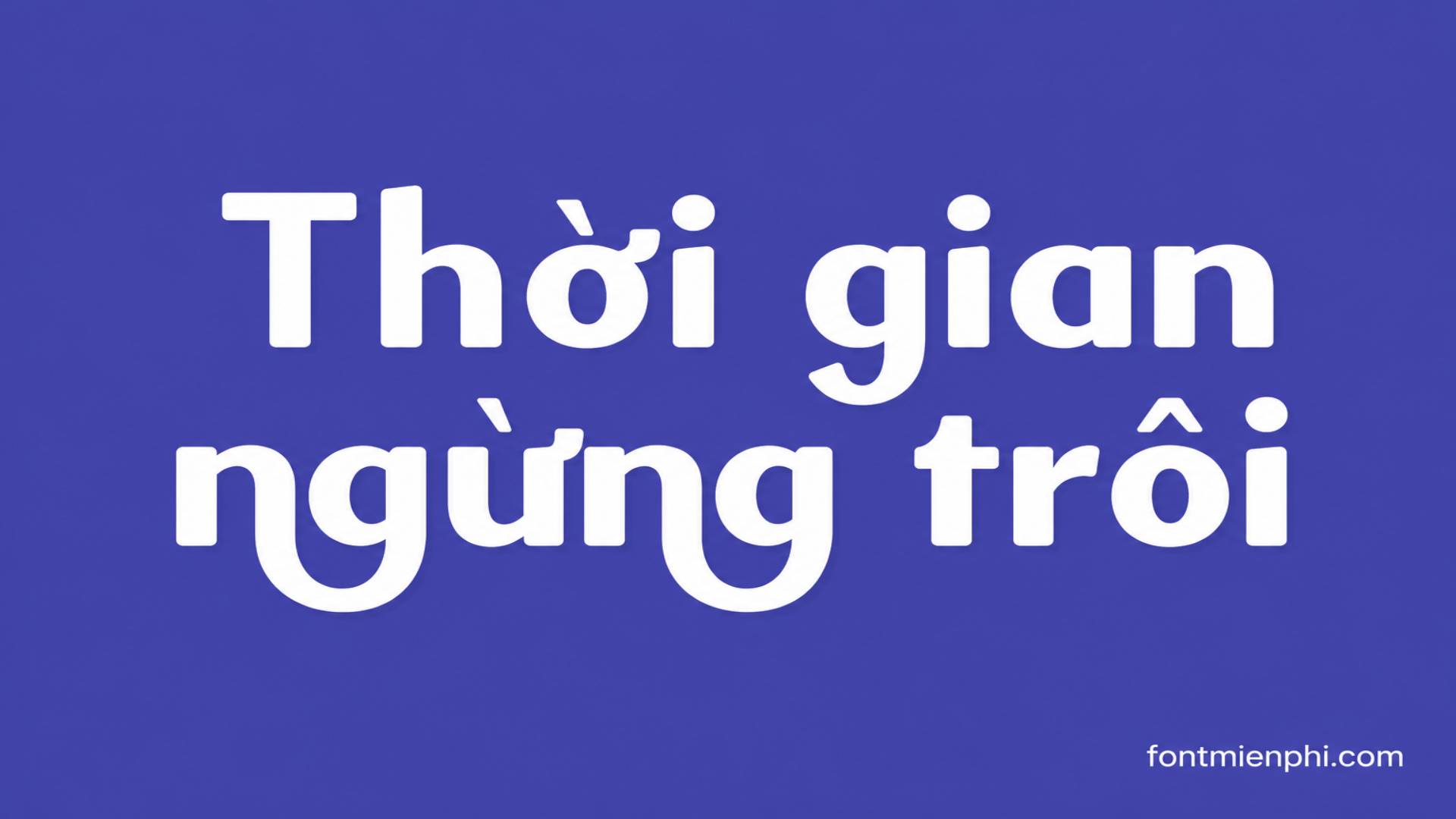
Bạn là một Content Creator, Designer hay Video Editor đang tìm kiếm một phông chữ hiện đại, cá tính để làm nổi bật các dự án sáng tạo của mình? Font Việt hóa 1FTV Creator Genius sinh ra chính là để dành cho bạn. Đúng như tên gọi “Thiên tài sáng tạo”, bộ font này mang đến một luồng gió mới với những đường nét phá cách, khỏe khoắn nhưng vẫn giữ được độ sắc nét và dễ đọc tuyệt đối.
1. Tổng quan về Font 1FTV Creator Genius
1FTV Creator Genius là một phông chữ mang phong cách hiện đại, năng động và đậm chất công nghệ. Khác với những phông chữ truyền thống cứng nhắc, Creator Genius được thiết kế với các đường nét dứt khoát, hình khối rõ ràng, tạo ra một nguồn năng lượng thị giác mạnh mẽ. Đây là kiểu chữ hoàn hảo để thu hút sự chú ý trong kỷ nguyên của mạng xã hội và nội dung số.
Hiểu được nhu cầu thiết kế đa dạng của người dùng Việt, đội ngũ 1FTV đã tiến hành Việt hóa chi tiết bộ font này. Hệ thống dấu câu tiếng Việt được vẽ lại tỉ mỉ, đảm bảo tỷ lệ cân đối với các chữ cái gốc. Sự tinh chỉnh này giúp người dùng dễ dàng gõ các tiêu đề, thông điệp bằng tiếng Việt một cách mượt mà mà không lo gặp lỗi “nhảy” font hay lệch dấu.
2. Những điểm sáng của Font Creator Genius Việt Hóa
Bộ font này nhanh chóng chiếm được cảm tình của giới thiết kế đồ họa và làm video nhờ những ưu điểm nổi bật sau:
• Phong cách sáng tạo, dẫn đầu xu hướng (Trendy & Modern): Mang đậm hơi thở của tương lai, công nghệ và sự phá cách, giúp thiết kế của bạn thoát khỏi sự nhàm chán thường thấy.
• Tối ưu hiển thị kỹ thuật số (Digital Display): Cấu trúc chữ được tính toán kỹ lưỡng để hiển thị cực kỳ sắc nét trên mọi loại màn hình, từ smartphone nhỏ gọn đến màn hình máy tính độ phân giải cao.
• Kerning Tiếng Việt chuẩn xác: Khoảng cách giữa các ký tự có dấu được xử lý hoàn hảo, không bị đứt gãy hay chồng chéo lên nhau, mang lại trải nghiệm đọc dễ chịu.
• Dễ dàng kết hợp: Là một phông chữ có cá tính mạnh, Creator Genius dễ dàng đóng vai trò trung tâm trong mọi bố cục thiết kế.
3. Ứng dụng thực tế của 1FTV Creator Genius trong thiết kế
Với tinh thần năng động và đột phá, Font 1FTV Creator Genius là công cụ đắc lực cho hàng loạt các dự án sáng tạo:
Mẹo thiết kế (Design Tip): Để tối ưu hóa sức mạnh của Creator Genius, hãy sử dụng nó làm Font chữ chính cho các Tiêu đề (Heading, Title) với các gam màu tương phản mạnh (Neon, Vàng, Trắng trên nền tối). Kết hợp với một phông chữ không chân (Sans-serif) cơ bản, dễ đọc cho các đoạn văn bản mô tả phụ.
• Thiết kế Thumbnail YouTube & Bìa Video: Giúp tiêu đề video giật gân, to rõ và thu hút người xem click ngay từ giây đầu tiên.
• Typography cho Video TikTok, Reels, Shorts: Hoàn hảo để làm phụ đề (subtitle) nhấn mạnh, các câu hook bắt tai trong các video ngắn đang viral.
• Nhận diện thương hiệu (Branding): Rất phù hợp để thiết kế logo, bộ nhận diện cho các Startup công nghệ, các công ty truyền thông, Agency quảng cáo hay các Studio game.
• Thiết kế Poster & Banner sự kiện: Áp dụng cho các sự kiện Workshop công nghệ, hội thảo Marketing, giải đấu Esport hoặc các chương trình âm nhạc hiện đại.
• Thiết kế UI/UX: Tạo điểm nhấn cho giao diện ứng dụng di động hoặc Website ở các phần Hero Banner, Call-To-Action (CTA).